如今,这些元素之中又多了一位新成员——字体。
相较于图片、文字, “字体”从视觉的呈现方面似乎无足轻重,但字体本身的表现力却不容忽视。我们可以发现,无论是焕新形象或是制造噱头,品牌推出专属字体早已不是一件新鲜事了。
然而,“专属字体”这番操作到底是多此一举还是锦上添花?不妨让我们盘点一些具有代表性的品牌字体,一起探索专属字体对于品牌的意义吧。
喜茶成立“造字局”
再现品牌会玩属性
作为新式茶饮的代表,喜茶近几年的成绩不同凡响,不仅先后几次获得资本青睐,市值估价160亿,还在营销上玩的风生水起,跨界联名更是手到擒来。据不完全统计,从2017年至今,联名的品牌超过50个,跨界范围囊括了食品、服饰潮牌、文创、生活用品、美妆护肤等诸多热门领域。
最近,大胆的喜茶再次与汉仪字库合作,共同成立了「喜茶字造局」,并联手打造了 92 款喜字组成 「微型囍书」和「十全十美书签」,页页皆喜,喜喜不同;一书一签,皆为喜字,让你「喜上加喜」。
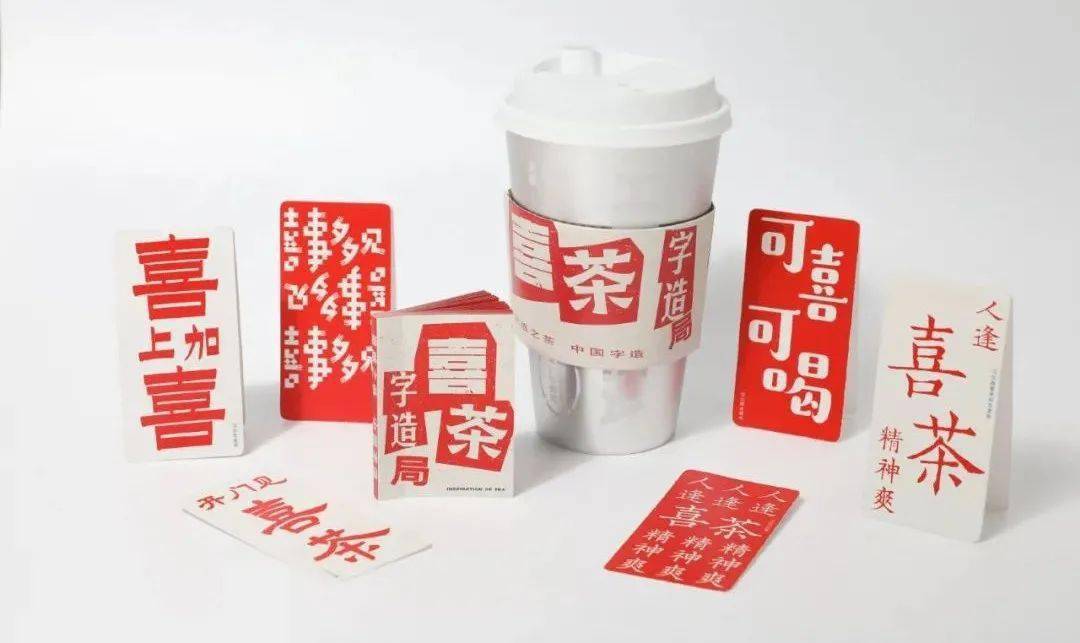
喜茶不是在联名就是在联名的路上,如今更是联名汉仪字库让字体从“素材”进化成“文化”。喜茶将中华文化的“喜剧审美”属性与品牌中的“喜”字进行创意改革,让文字不再只是一种素材,还成为与不同文化交互、不同品牌对话合作的媒介。
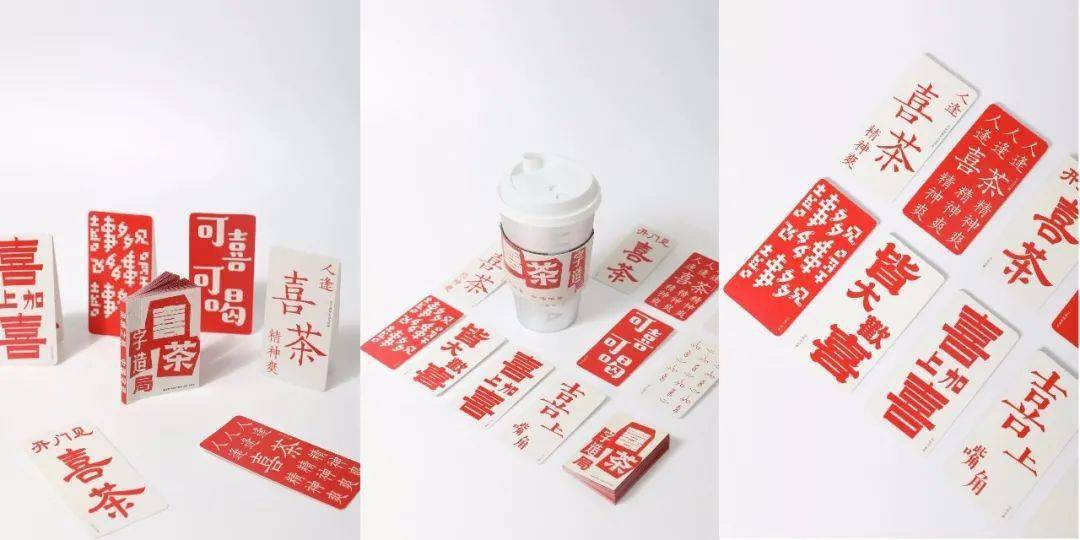
喜茶推出的这组专属字体,都是常用的熟悉字,而且“喜”字的红色与奶茶色的混搭,充分展现了喜茶品牌会玩的调性,也深得喝奶群众的一致好评:
总之,喜茶联合汉仪字库打造“造字局”,既弘扬了中国的汉字文化,又因为喜字与喜茶有着直接关联,加深了对自身品牌的突出,并在恰当的时机下,为自己进行了一波贴切的品牌传播。
打造专属字体
已成为品牌营销的标配
近两年,谈论字体设计的人越来越多,字体版权维护也越来越常见,字体传达的信息也越来越广。不少品牌都尝试推出专属字体,不只为传递有效的品牌信息,还承载着传达品牌价值观、精神的核心理念。
除了喜茶此次的“造字局”计划,可口可乐、腾讯、阿里巴巴、方太等各大品牌,也早就开始布局字体设计,推出了自己专属字体。
比如可口可乐为庆祝进入中国 40 周年,通过方正字库特别推出了一套字体——「可口可乐在乎体」,字体除了吸取了中国的传统文化精髓,也结合了现代审美,笔画简约利落,折笔刚劲有力,整体状态劲健十足。字体取圆融与力量、进取之意,与「上善若水,水利万物而不争」之意相呼应,这也是可口可乐对公司文化的理解和定位。
方太也曾发布了自己的品牌专属字体——“方太梦想宋”。字体基于雕版体开发,创作时从大量雕版资料从中寻找字体原型,以“形、意、度”为标准着手,形即结构,意即神态,度即平衡,让方太梦想宋逐步成型。 这套字体共有三个字重,字形修长,笔画方折,重心略向右上翘,秀丽而不失风骨。
除此之外,阿里巴巴也曾推出了普惠体,以 9 个品牌体感词为切入点,将体感共鸣转换为字体造型;OPPO在品牌20年之际打造了OPPO Sans字体,配合品牌升级的整体方向, 将“科技美感、探索精神、全球视野”概念灌输到字体之中,以视觉语言表达...
打造专属字体俨然已经成为品牌营销的趋势,那么众多大牌为何热衷此道?
1、减少宣传成本,避免侵权行为
近些年来,随着大众版权意识的提高,版权方的维权力度也越来越大。其实,我们日常使用的方正、汉仪等字体,很多都属于有版权的字体,是不可以商用的。
而因字体非法商用导致的侵权事件屡见不鲜,导致企业和品牌频频中招,财务和品牌形象双双受损。而品牌自己设计字体,就能避免侵权行为的发生。同时,品牌的专属字体也可为品牌减少更多宣传成本,实现低成本营销。
2、提升品牌辨识度,强化品牌价值传播
随着品牌竞争的日益激烈,想要强化大众对于品牌的认知,就要不断尝试将具象的元素与品牌进行强关联。而品牌字体除了可以在视觉和设计上为品牌加分外,字体本身也可以成为品牌传播的契机,重塑或升级品牌形象,深入传播品牌理念。
就比如喜茶成立的“喜茶字造局”,对“喜”字的不断延伸,从而让其在社交媒体上形成话题传播,最大化吸引用户注意力,同时也精准传递了喜茶品牌的品牌理念,一举两得。
3、形成统一视觉体系,积累品牌资产
同时,独特的品牌字体也具备超高的高辨识度,辅助品牌形成一个既强烈且统一的形象,让受众在阅读时对品牌产生更直接的联想。
毕竟品牌形象的塑造是一个漫长且艰难的过程,不仅需要持久的资源投入,更需要通过各种方式为品牌添砖加瓦。一个独特的品牌名让人印象深刻、一个充满设计感的Logo让人眼前一亮、一个醒目的品牌色让人记忆犹新,同样一套差异化的品牌字体也能直达受众的心灵,引发共鸣。
就比如可口可乐的“在乎体”,不仅仅是客观的传递文字的表面信息,还借助文字设计传递品牌强烈的情感和力量,承载起传播品牌精神的重任。
注意力时代
专属符号才是品牌的护城河
这是一个信息爆炸的时代,注定就是注意力高度稀缺的时代,在如此巨大的冲突之下,消费者的注意力只有短短的8秒,因此在越来越以速度为导向的营销战役中,视觉的作用日渐放大。
这对于品牌来说,视觉的表达可以从品牌形象(专属符号)和品牌理念(核心竞争力)两个层面进行构建——向消费者展示你是谁,然后告诉消费者你能解决他们什么冲突;两者缺一不可。
品牌形象的构建,是品牌立足于市场的基础,除了名字、颜色LOGO外,字体的价值也在不断被放大,也成为了品牌的识别符号之一。那么品牌该如何正确运用字体营销呢?
1、注入文化价值,让字体更具生命力
以文抒情,以字达意。品牌专属字体除了广泛应用于广告宣传外,还承载起传播品牌文化的重任的。因此,品牌字体的设计理念必须匹配品牌的核心价值观,需要保持品牌一致性,要做到“知行合一” 。
比如方太的品牌字体“方太梦想宋”,其背后的故事来自于一位姓宋的母亲,年轻时的梦想就是创造一套字体,坚持多年仍未放弃,最终在方太的助力下圆梦。这个故事的包装让品牌字体的发布不再单调孤立,而是为其注入了品牌价值,成为品牌整体塑造的重要一环。
2、增加消费的仪式感,融入消费者日常生活
日常生活中,人们离不开文字的使用,正是如此,品牌打造专属字体能够以「润物细无声」的姿态浸润在人们的生活中。而字体还可与产品进行有效融合,给品牌消费带来一种仪式感。
比如可口可乐打造的“在乎体”,除了让个人免费使用外,还印在了可口可乐的定制罐上,这不仅是可口可乐给品牌自身的一种仪式感,也是可口可乐赋予消费者的一种仪式感,从而刺激消费者为这份仪式感来买单。